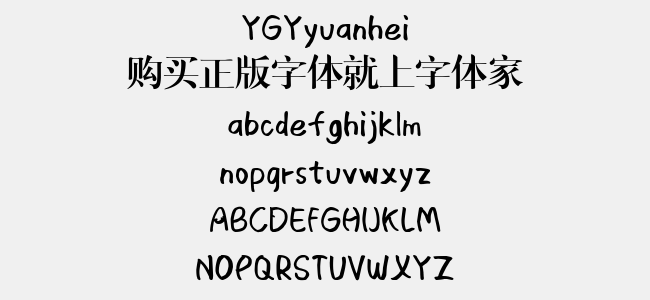
YGYyuanhei
字体作者:YGY-ywtixi
字体名称:YGYyuanhei
字体字数:26个英文大小写字母及和阿拉伯数字
字体家族:YGY-ywtixi
书体类型:英文类
字体作者:YGY
YGYyuanhei
YGYyuanhei是一款个性独特的英文字体,由YGY-ywtixi制作发布,非常适合创意类的PS字体,英文广告设计载体上使用,在设计中选择这款字体应用的话,会起到非常理想的效果。